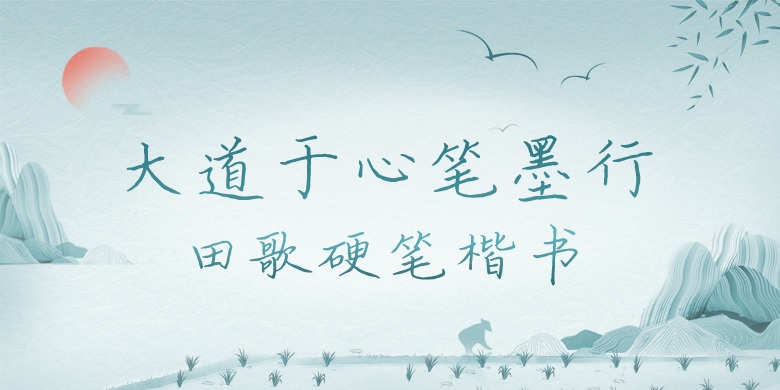
字体介绍 品牌:方正手迹 设计师:田歌发行时间:2019字库编码:大陆简体(GB2312-80)分类:常规书写·硬笔 英文名称:FZSJ-TGYBKSJW.TTF 田歌曾因一则“女孩书法惊艳如字帖”的新闻而刷爆朋友圈。田歌硬笔楷书继承自传统书法,很好的传承了书法文化。结字秀逸,笔势拿捏恰到好处,用笔游刃有余,颇有古小楷之韵。适用于文艺类的书刊、品牌广告和产品包装设计,以及社交网络的个性化用字。 字体下载 官方下载